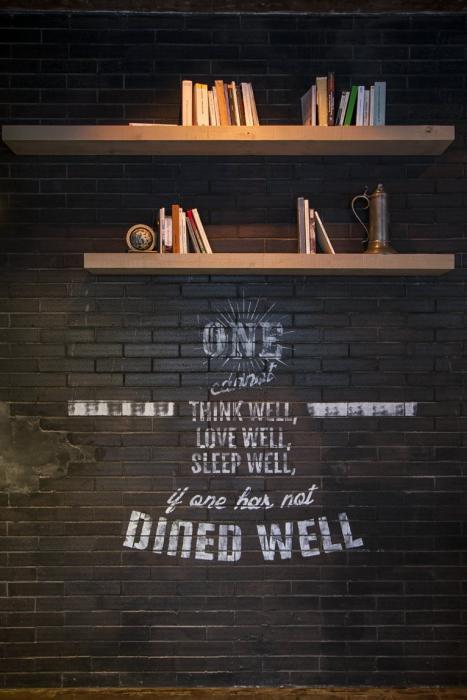
Tafelschrift mit "rundem großen N" gesucht
ich suche die Schrift des Schriftzugs ganz unten ("Dined well"). Die Schriftarten, die ich bisher gefunden habe, haben entweder nicht das "große N", das mit der Rundung so aussieht wie ein kleines "n", oder das "W" ist geschwungen.
Das N aus DINED ist ein gedrehtes U. Das "originale" N sieht man in THINK.
Zudem glaube ich, das dieser Tafelschrift-Effekt, also das Kreidige dadurch kommt, dass hier eine Schablone (könnte eine Folien-Plot gewesen sein) mit einer ziemlich trockenen Farbrolle auf die Wand gerollt wurde. Es sich also nicht um diese offenporigen Kreideschriften handelt.